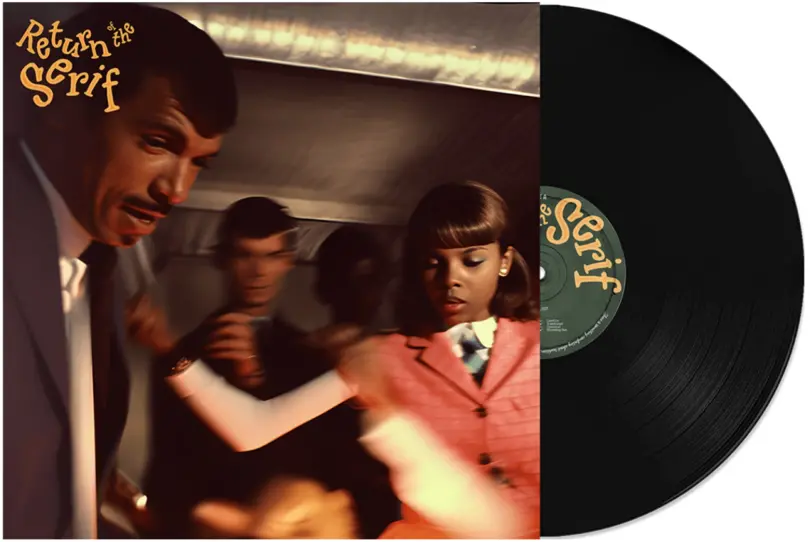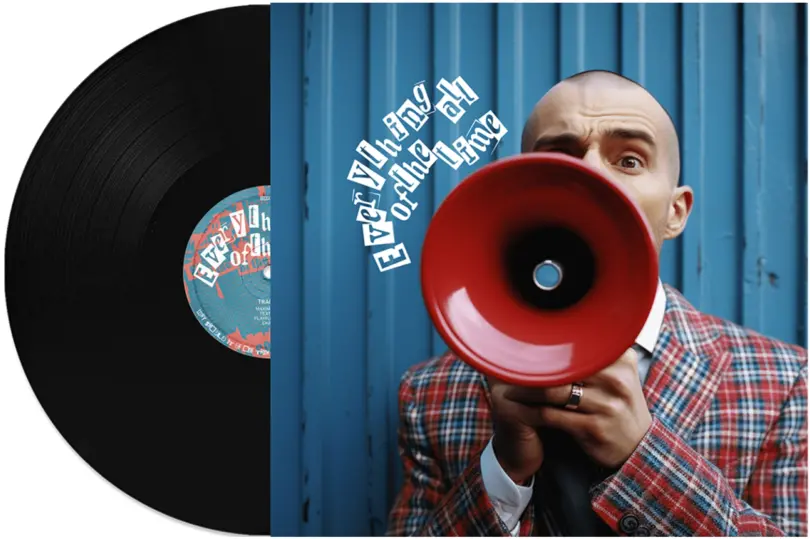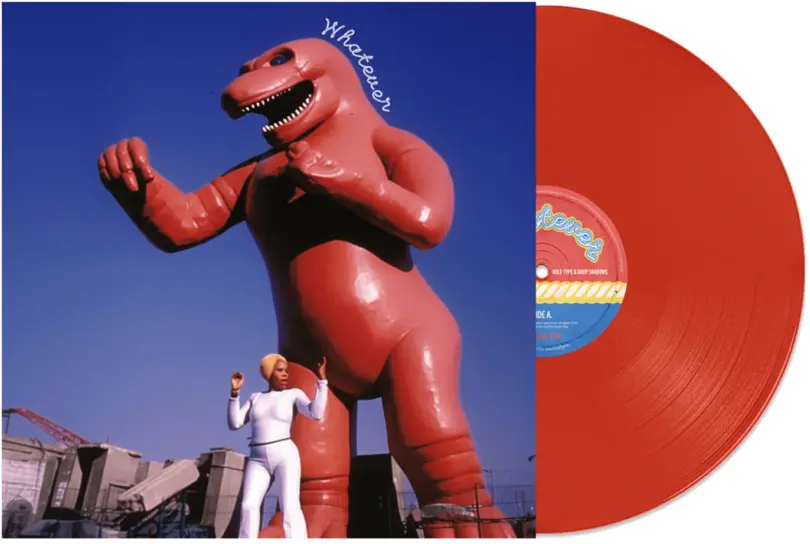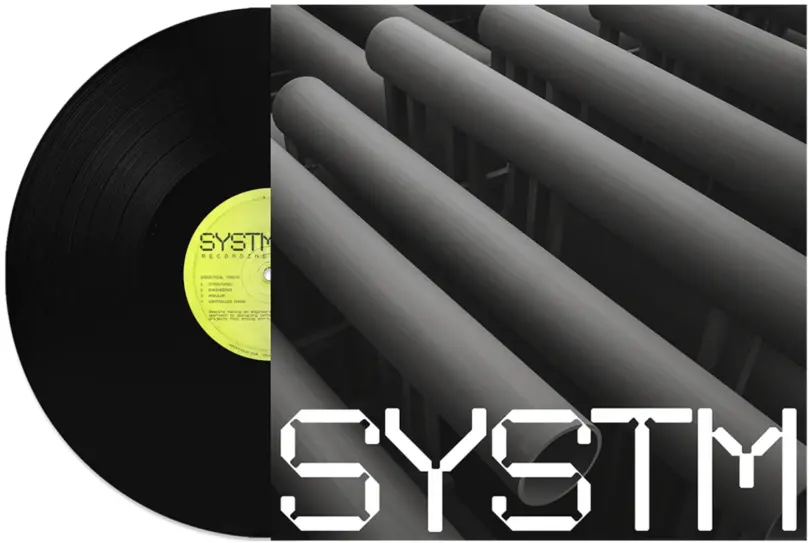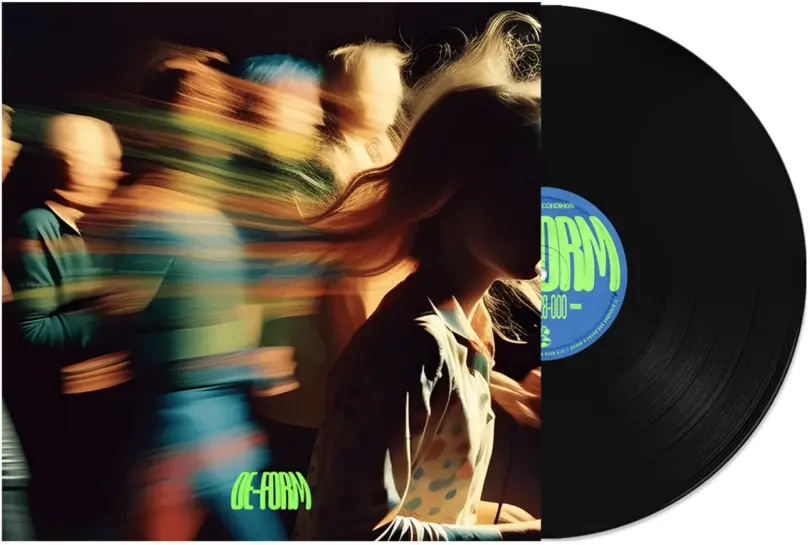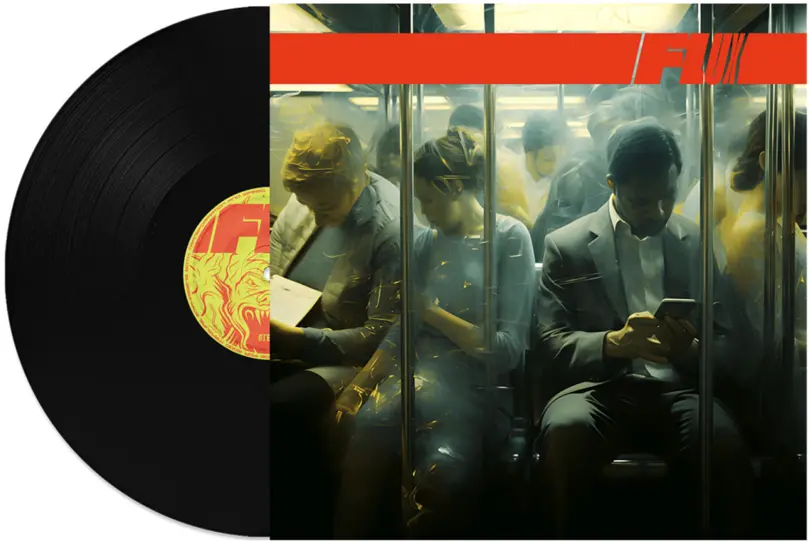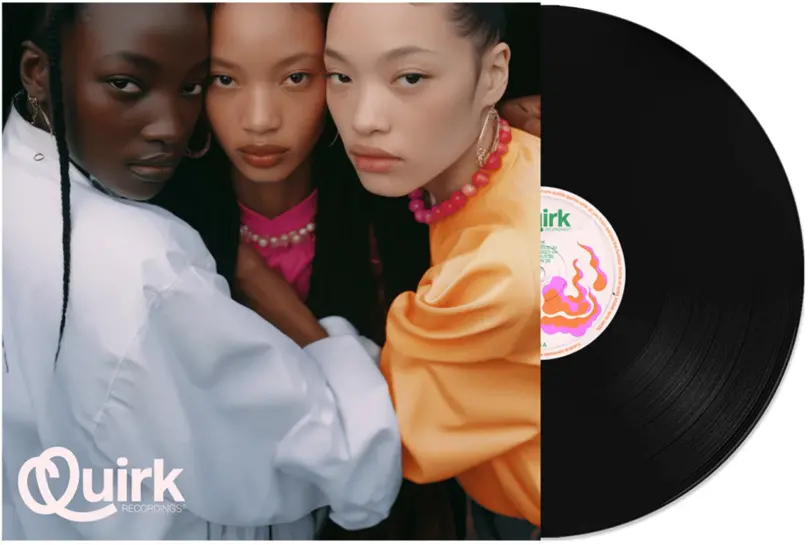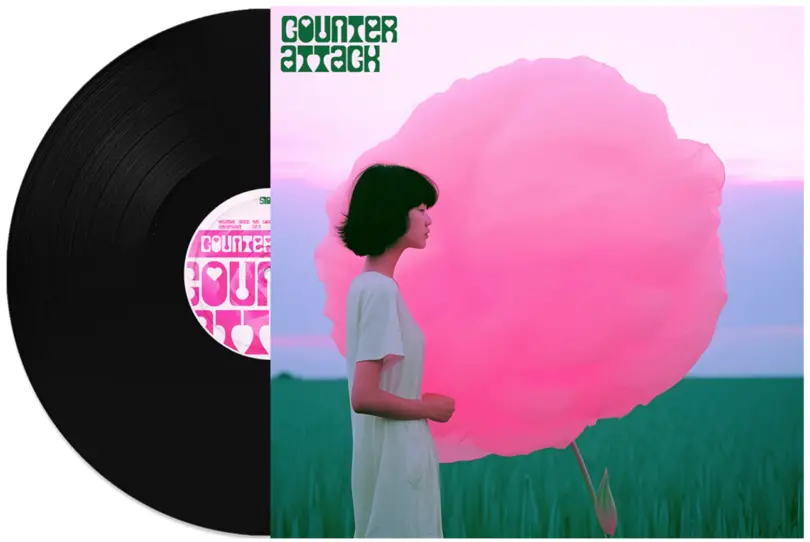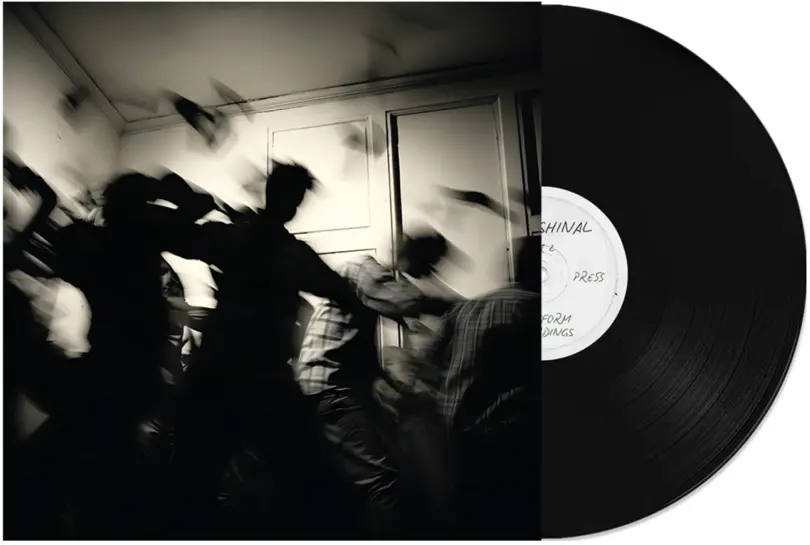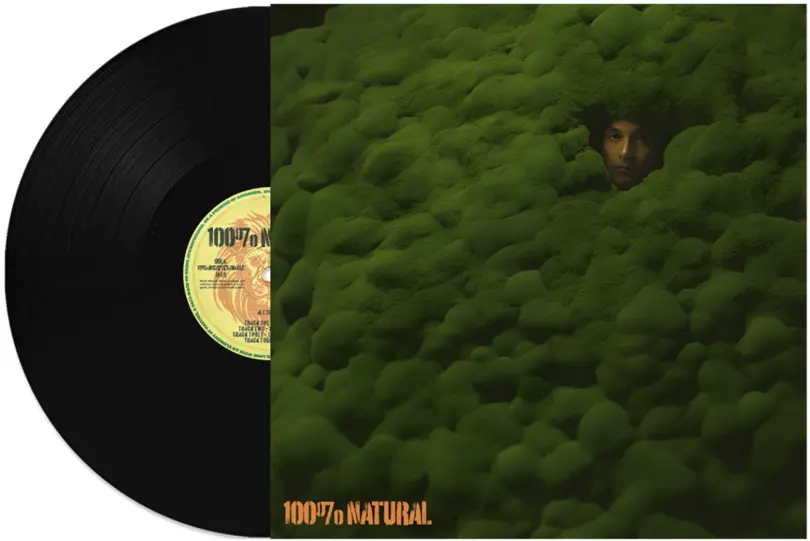
成功するブランドは書体から:最新のタイプトレンドレポート公開
Monotypeが年に一回発表している「Type Trends Report」の日本語版を本日より一般公開しました。 今年のレポートでは、書体がどのように社会と結びついているのかを探るため、世界中のクリエイティブな作品を参照し10のトレンドを事例とともに紹介しています。また本資料では、日本と中国にフォーカスしたトレンド情報も追加掲載しています。
書体が語る2024年のトレンドとは
毎年恒例のMonotypeのタイプトレンドレポートは、私たちの身の回りにあるユニークなタイポグラフィが何を伝えようとしているのか、耳を傾ける機会を与えてくれます。デザイナーの作品は何を現し、何を伝えようとしているのでしょうか?そして、なぜそれらを素晴らしいと感じるのでしょうか?
Everythingallofthetime.
いつでも、全て、同時に
もし書体が今日の私たちの生活について何かを伝えるとすれば、この最初のトレンドは、生活のありとあらゆる面を、あらゆる場所で、同時に影響を受けているということです。
Whatever.
何でもあり
90年代のノスタルジーから生まれたWhateverは、虚無的なグランジからカラフルなピクセル・プレイまで、さまざまなスタイルを網羅しています。
Systm.
システム
文字をデザインする際のエンジニアリング的側面やアプローチを持っているにもかかわらず、アナログで人間らしい印象を与えます。
De-form.
規格外
De-formは、書体の基本構造を壊し新しいデザインを表現しています。
Flux.
可変性
アニメーションによって作られているのか、動きからインスパイアされているのかに関係なく、スピーディでダイナミックなデザインを表現しています。
Quirk.
風変わり
何か予想外のことを試してみる意欲、目立ちたいという意欲、異なる方法で話す意欲をデザインしています。
Counter Attack.
意外性
余白スペースを存分に生かしたデザインに注目。これまでにない楽しく自由な書体を表現しています。
Profeshinal.
プロフェッショナル
ユーモアと正直さを慎重にブレンドさせ、好奇心を掻き立てるが、同時に素晴らしい創造物へと導きます。
100% Natural.
100%ナチュラル
文字作りの喜びを祝い、持続可能なマインドセットで言葉を戦略的にデザインしようとしています。
Return of the Serif.
セリフ体の回帰
伝統には何か安心感があります。それは、ますます複雑な環境の中で地に足をつけて表現する事の大切さを教えてくれます。